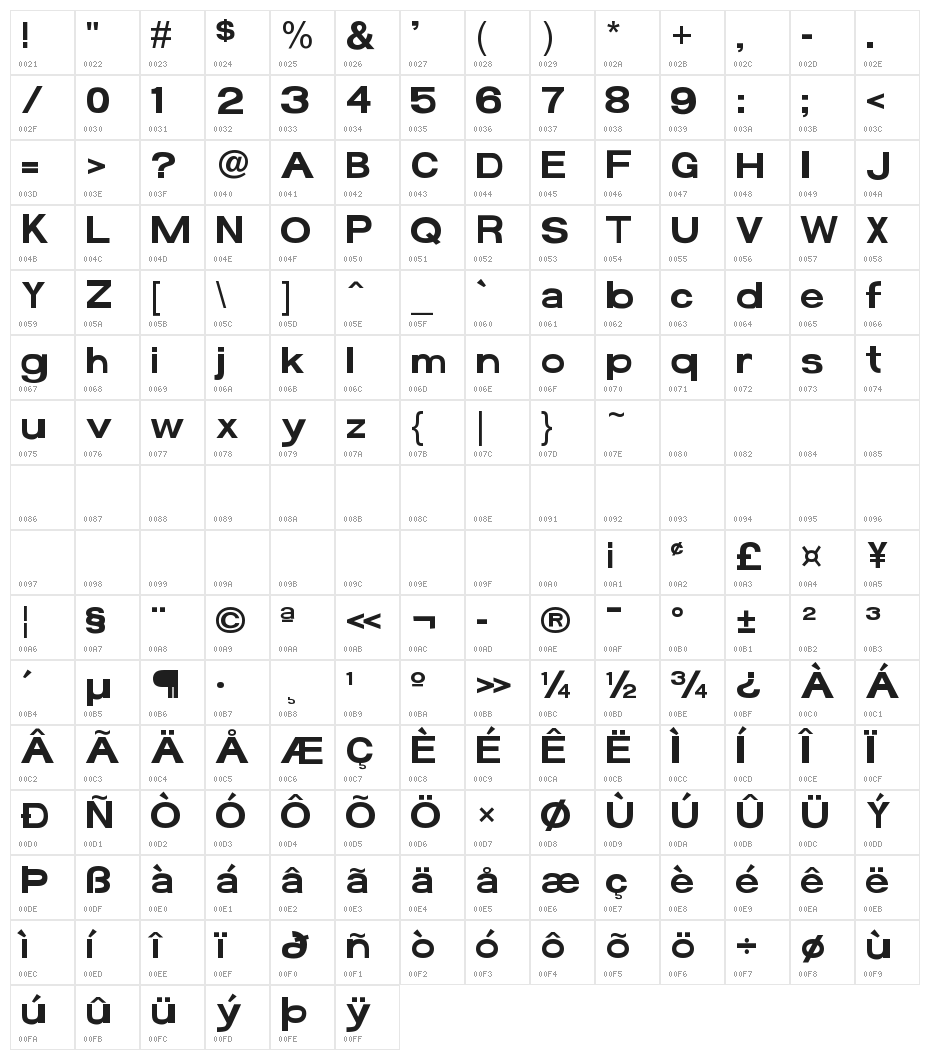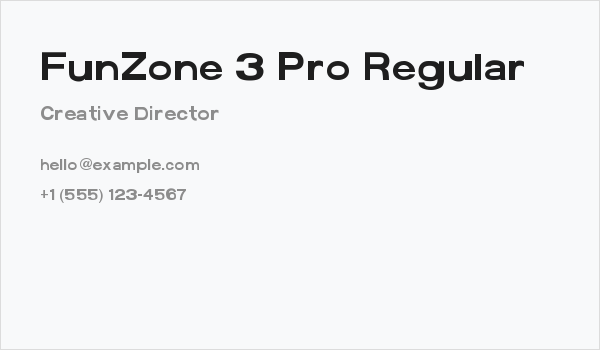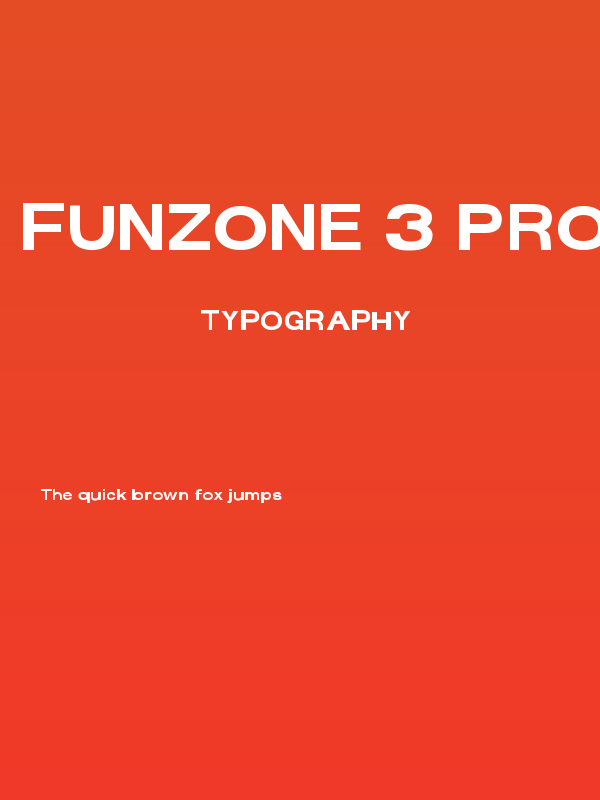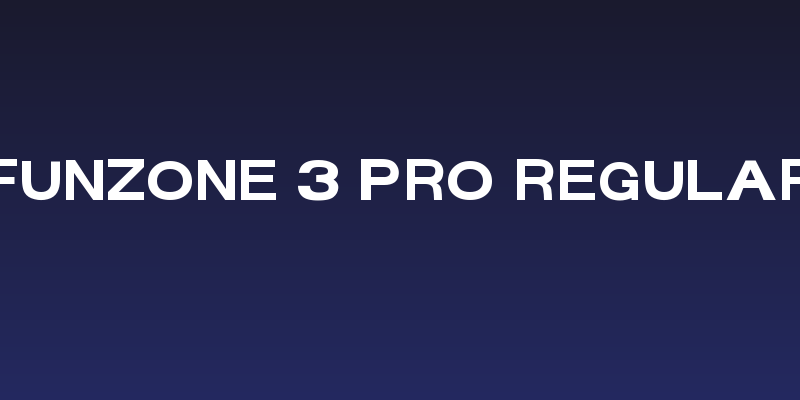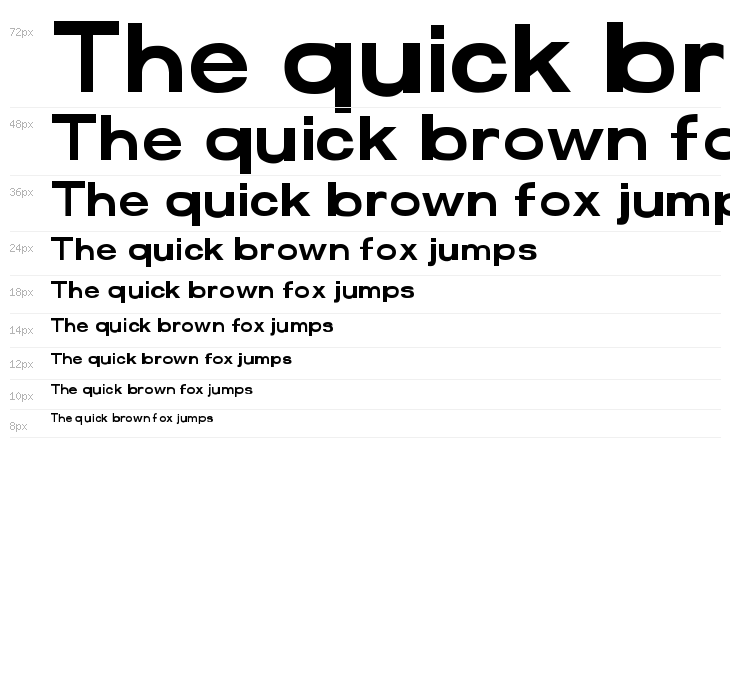
FunZone 3 Pro Regular Font
| Caso d'uso | Headlines, Logos, Branding |
| Progetti proposti | Ideal for branding, advertising, headlines, and digital content where a strong, modern impression is desired. |